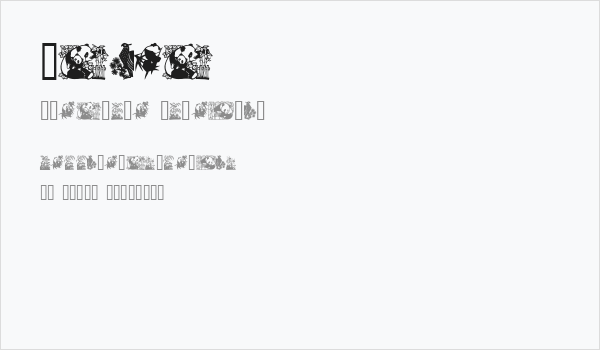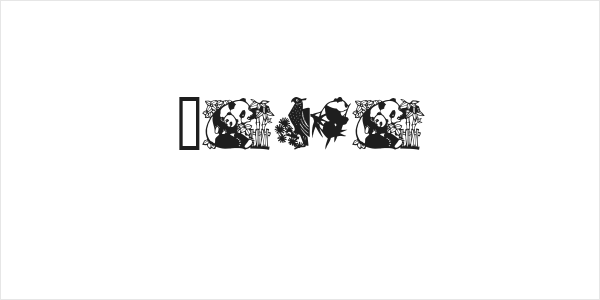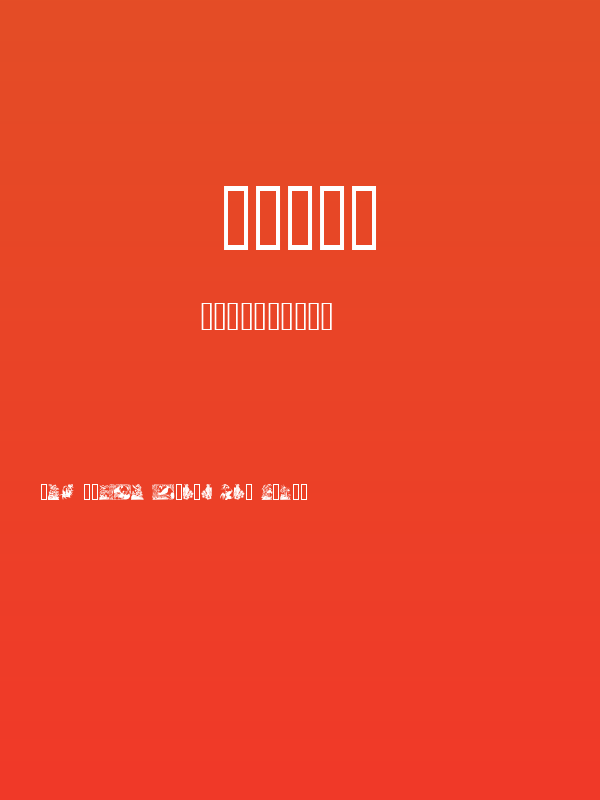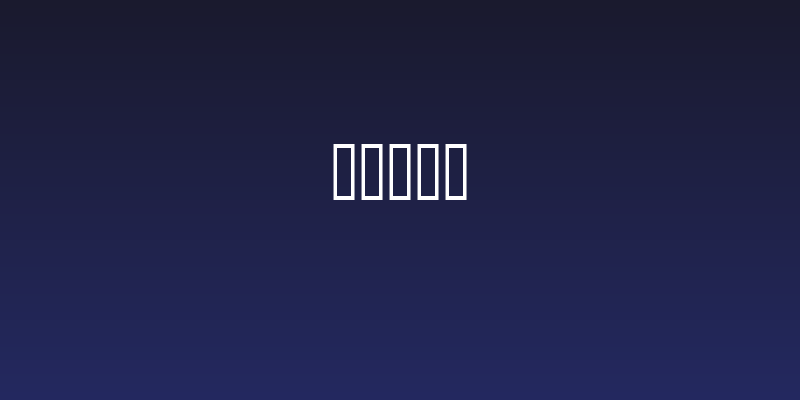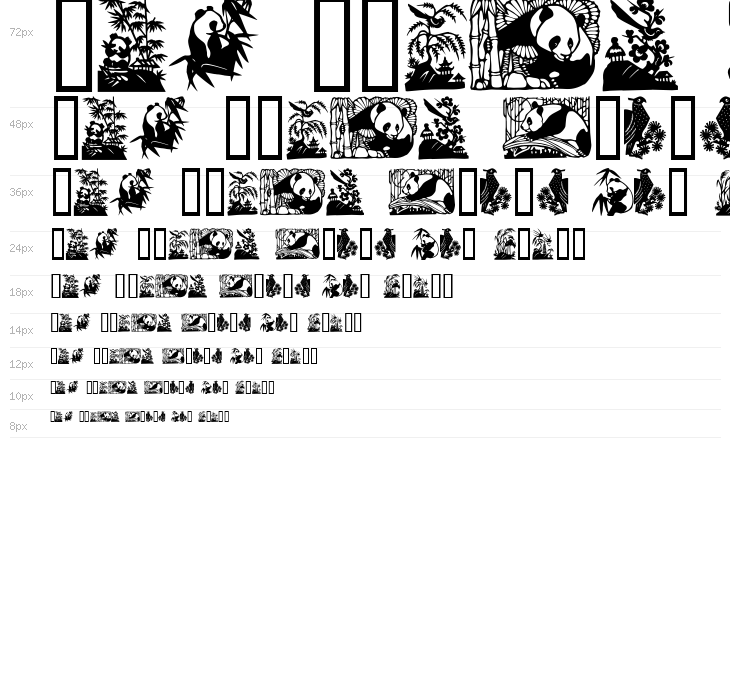
Panda Font
✎ Dingbats
| 用途 | Artistic designs, decorative purposes, educational materials. |
| おすすめプロジェクト | Ideal for creative projects such as children's books, nature-themed posters, or educational materials about wildlife conservation. |